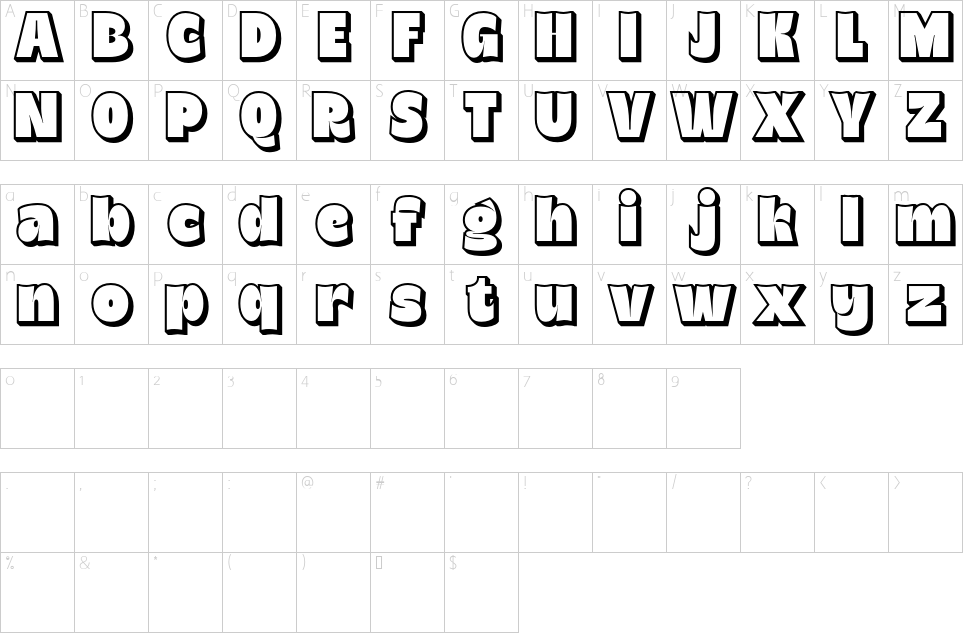
Almie Font
A fonte Almie oferece uma experiência gráfica envolvente para designers que buscam um estilo moderno e elegante. Desenhada pela Craft Supply Co, a Almie vem em versões para Windows e Mac e tem sido adquirida por 233 pessoas. Suas linhas fluidas e harmoniosas permitem criar textos de alta qualidade e sofisticados materiais de design. Ideal tanto para aplicações comerciais quanto para projetos de arte digital, a Almie é uma escolha inteligente para quem busca uma fonte de alta qualidade sem precisar desembolsar grandes quantias. Engajada e versátil, a Almie está pronta para revolucionar sua próxima grande obra de arte.
Mapa de caracteres da fonte Almie Font